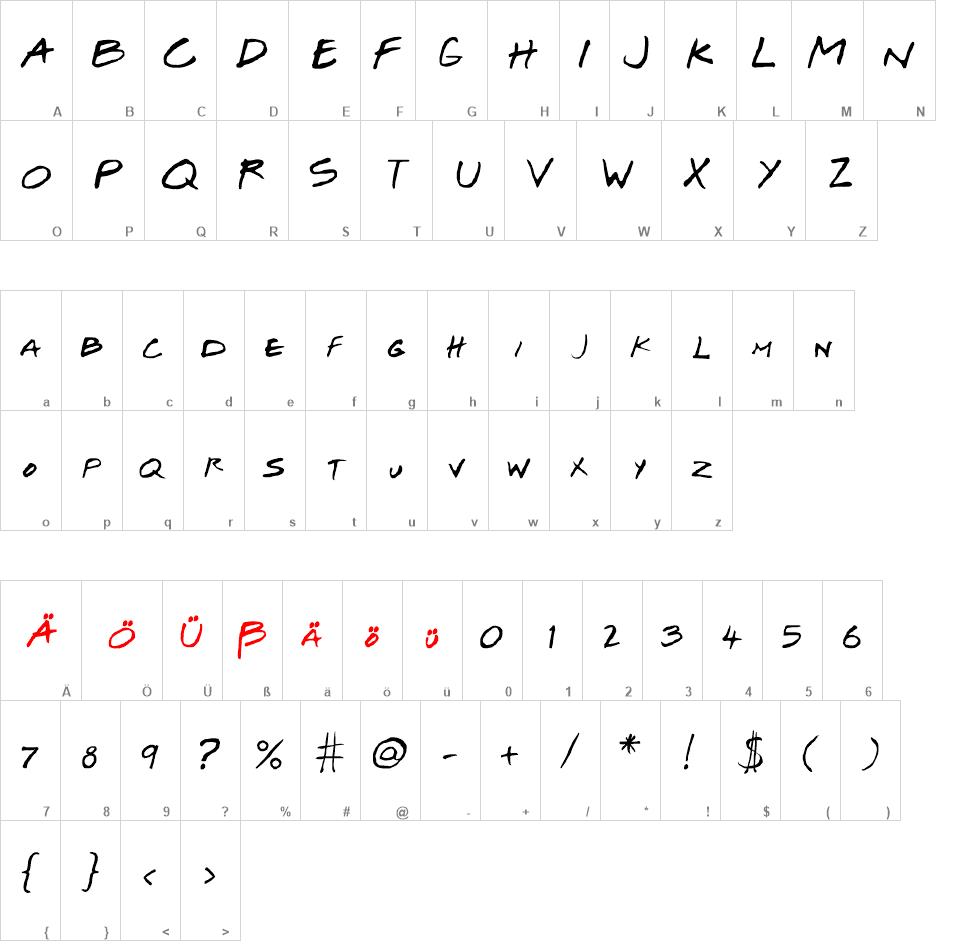
Josef Xuereb's Friends
Ich hatte das Bedürfnis, diese Schriftart zu erstellen, weil ich nie wirklich eine Friends-Schriftart gefunden habe, die der in der TV-Serie verwendeten entspricht. Nun, das ist es!
Es kommt in 4 Variationen:
* Regular, enthält große und kleine Kappen;
* Kursiv, enthält nur Kapitälchen;
* Fett, enthält nur große Kappen;
* Fett kursiv, enthält eine aufrechte Version der Schriftart.